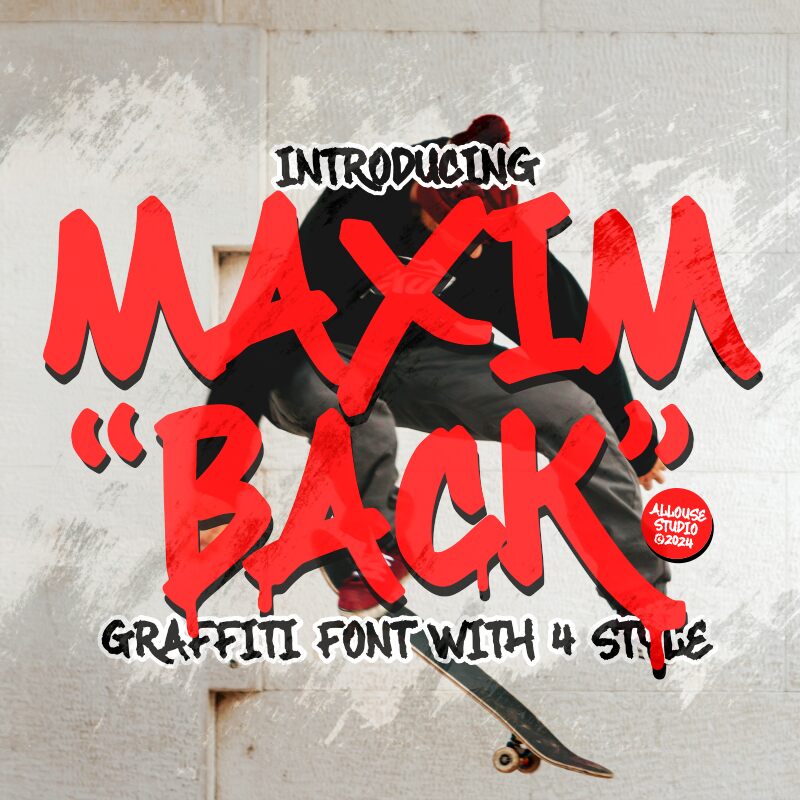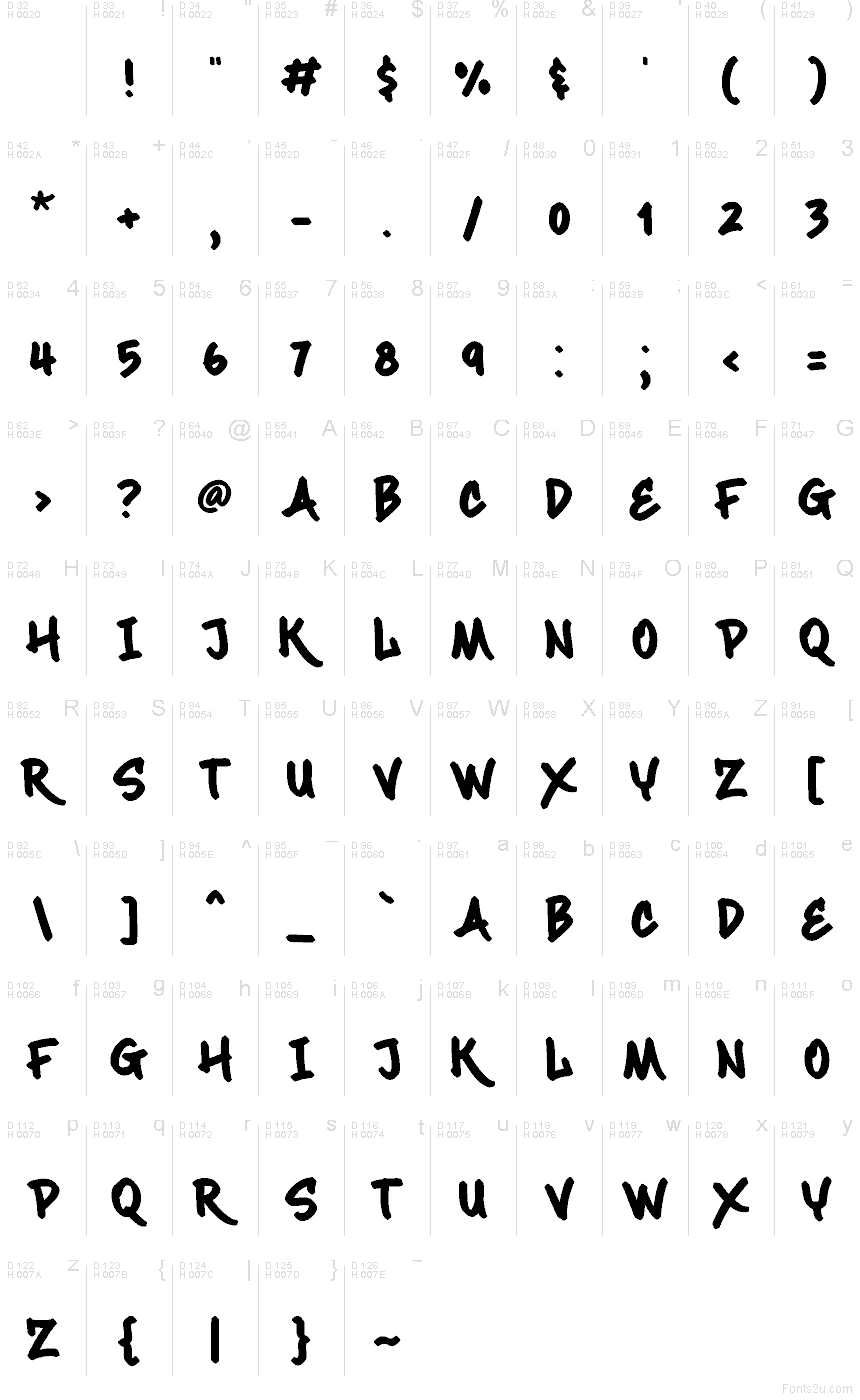
تعد Maximback من Allouse.Studio خط جرافيتي مجاني، يتشكل من خلال ضربات سريعة تشبه قلم التحديد وإيقاع عفوي مستوحى من كتابات الشوارع (Street-tag). الوصلات المسننة، والقطع الزاوي، والارتداد غير المنتظم قليلاً يحافظ على طابع الحروف الخام والعفوي، بعيداً عن المظهر المصقول أو النظيف الخاص بالشعارات.
تعتبر هذه الخطوط مثالية للملصقات، وأغلفة الألبومات، وتصاميم لوحات التزلج، ومنشورات الفعاليات، وعناوين وسائل التواصل الاجتماعي، خاصة عندما يحتاج التصميم إلى تلك الطاقة المستمدة من الكتابة اليدوية على الجدران. تستفيد العناوين القصيرة والعلامات التجارية ذات الطابع الحضري بشكل أكبر، لأن التدفق الخشن للضربات يمنح كل كلمة شعور التوقيع السريع بدلاً من مجرد عنوان عرض محايد.